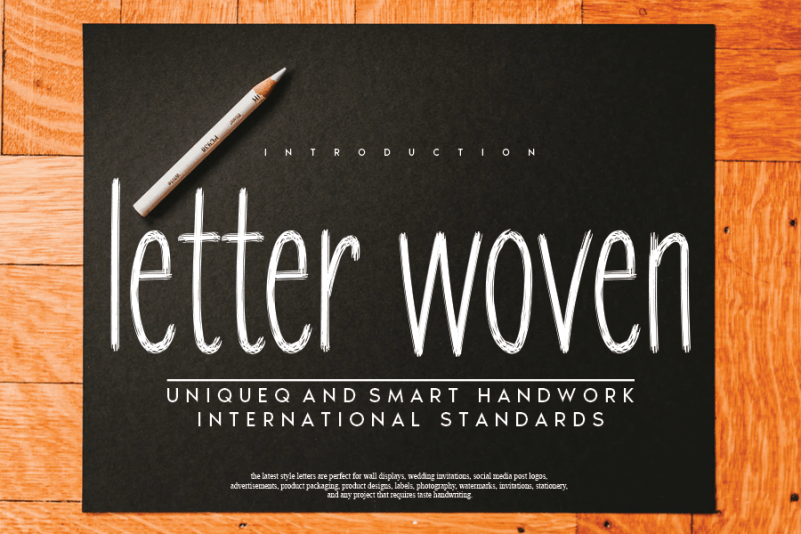
letter woven Handwritten Font – Download Grátis
A fonte ‘letter woven Handwritten Font’ é uma ótima escolha para quem busca adicionar uma sensação natural e alegre a seus projetos digitais. Inspirada em escrita à mão, esta fonte tem um estilo único e envolvente que combina perfeitamente com diversos estilos de design. Ela se destaca por sua aparência suave e amigável, adequando-se perfeitamente a uma ampla variedade de tópicos de criação visual. O designer andikastudio desenhou esta fonte para permitir que os criativos utilizem seus conceitos imaginários ao máximo. Com a ‘letter woven Handwritten Font’, é fácil alcançar um resultado único, pois sua aparência natural e única permite uma liberdade de expressão sem precedentes. Aqui está um exemplo: um site de moda jovem pode aproveitar o charme deste estilo para criar mensagens personalizadas, ou até mesmo um projeto gráfico para a comunicação de marca. Com ‘letter woven Handwritten Font’, os profissionais de design estão sempre um passo à frente em suas criações digitais.